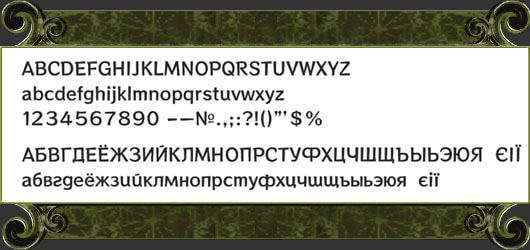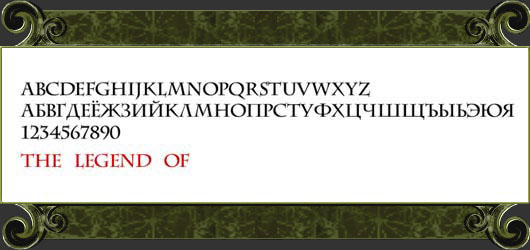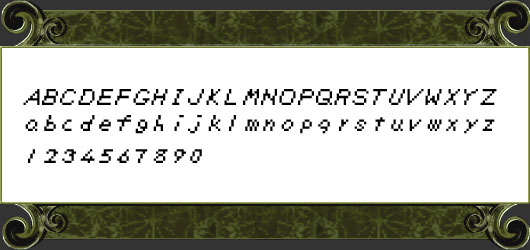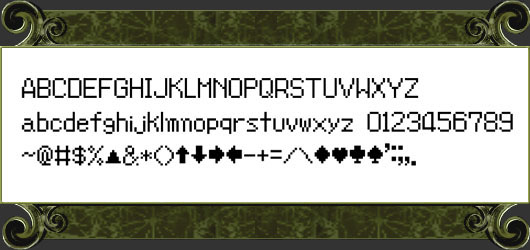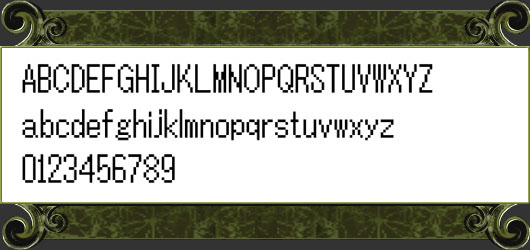
Reggae C
Используется в Wind Waker,
Four Swords Adventures, Navi's Trackers, Phantom Hourglass и Spirit Tracks в различных
надписях в интерфейсе.
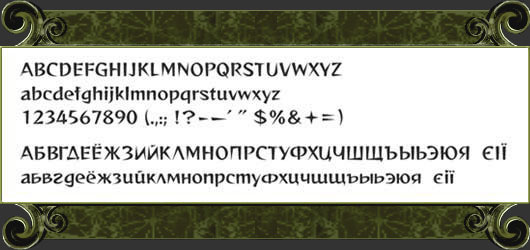
Rock & Roll C
Используется
в Wind Waker, Phantom Hourglass и Spirit Tracks в диалогах.
DFTF LeiSho
Используется
в Twilight Princess в именах боссов, названиях локаций и заголовках. В архиве
три шрифта: DFTFLeiSho-W5, DFTFLeiSho-W7 и DFTFLeiSho-W9. На картинке латинский
шрифт и примеры надписей набраны Fullwidth символами (Unicode, начиная с кода
FF01 и далее), шрифтом DFTFLeiSho-W5. Также в данном шрифте есть поддержка
японского языка.
Charlemagne
Шрифт, использующийся в надписи
"THE LEGEND OF" в некоторых играх, в надписях "oracle of Seasons/Ages",
возможно где-то еще.
Zelda
Используется
в самой первой игре в диалогах и прочих надписях.
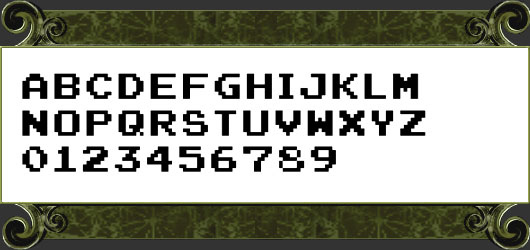
Nintendo NES
Используется
в играх Zelda на NES в диалогах и прочих надписях, а также во многих других играх
на Nintendo Entertainment System (NES).
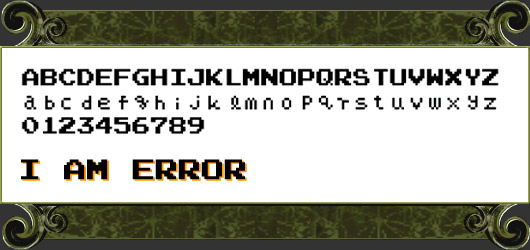
Return of Ganon
Используется
в Link To The Past в диалогах и прочих надписях.
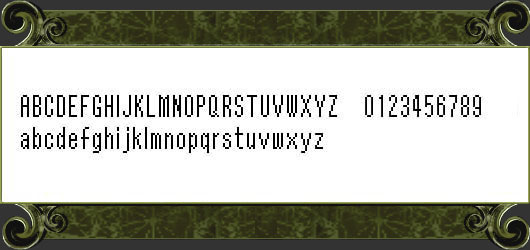
Zelda DX
Шрифт,
использующийся в Link's Awakening в диалогах и прочих надписях.
Zelda Oracles
Шрифт, использующийся в Oracle
of Seasons и Oracle of Ages в диалогах и прочих надписях.
Minish Cap
Шрифт, использующийся в Minish
Cap в диалогах и прочих надписях.
Triforce
Шрифт, использующийся в слове
"Zelda" в логотипах игр.
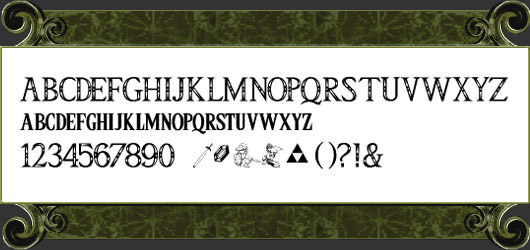
Ravenna
Используется
(с некоторыми изменениями) в надписи "Twilight Princess " в одноименной
игре.
Sherwood
Используется (с некоторыми
изменениями) в надписи "the Wind Waker" в одноименной игре.
Zapf International
Используется в логотипе самой
первой игры серии. В архиве два начертания шрифта, regular и bold. На картинке
показан bold.
Chiaro
Используется в Ocarina of
Time и Majora's Mask в диалогах.
Kokinedo
Используется в Ocarina of
Time и Majora's Mask в именах боссов и в надписи Game Over.
www.fontworks.co.jp. Воссоздал шрифт: Emarian.
Rodin
Шрифт диалогов Twilight Princess
и заголовков подменю в Ocarina of Time (N64) (В указанных играх используется
полужирное (bold) начертание данного шрифта).
Разработчик:
www.fontworks.co.jp. Воссоздал шрифт: Emarian.